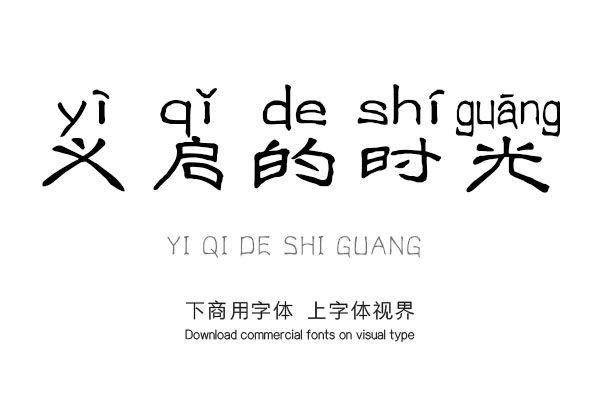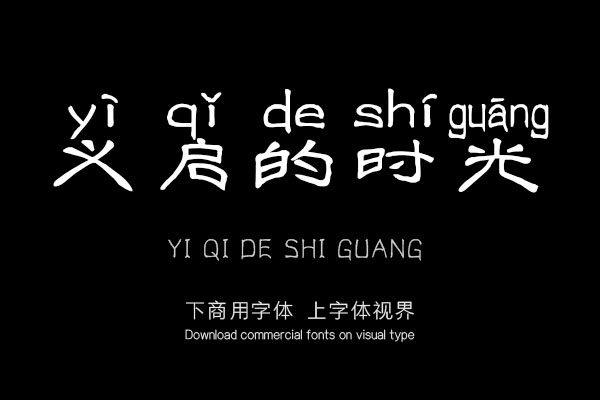
义启的时间是义启字库创作的一种可以免费试用字体的个性字体,字型上下松动,中间向上突出,下半部按弧度向左右两侧延伸。
这个字体的形状就像秦国的酒器:爵士。秦酒器的特点是上下宽而中窄,三足长而细,也符合义启时间这个字体的特点。看到这个字体,我们不禁想起秦朝的历史。隶书是汉字中常见的庄重字体,书写效果略宽扁,横画长而直画短,讲究蚕头燕尾、一波三折。起源于秦朝,东汉达到顶峰,书法界称之为汉隶唐楷。
而且这种义启的时间字体是以隶书为基础的,设计师在此基础上加入了适当的艺术效果,使之富有律动感,在笔画中减少了过多的处理和笔势,笔画的起落点比较丰满,字体造型既有现代感,又保持了原有的古朴风韵,具有很强的视觉冲击力。
经过几千年的发展和演变,中国的传统文化仍然具有很强的生命力,至今仍深深影响着中华民族。
设计师也是受中国传统文化影响,真诚热爱传统文化的人。他非常喜欢学习传统文化,所以在学习当代设计的同时,他不忘继承和发扬传统文化。在这种字体的塑造中,东方传统文化与西方美学元素相结合,相互碰撞,实现共生共融,最终产生这种字体。我们还需要向这种字体的义启字库设计师学习。我们可以利用义启时间的创意字体设计,充分发挥现代媒体的优势,加强传统文化精髓的提炼和传播!